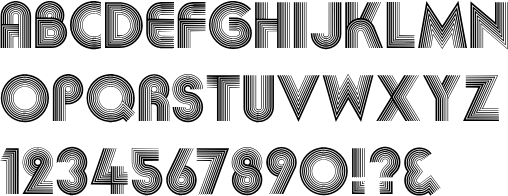
マイクロソフトの初代ロゴで使われた書体「アキラインズ」。「Computational
Geometry Lab」によると、日本人によるデザインのようです。本来、
オルタネートが存在しますが、デジタル化はされていません。現在は 「Linea」
とリネームされたフォントが販売され、「Akka」という無料のクローンフォントもあります。
| Microsoft Logotype in 1975 |
Aki Lines |
| Designers |
: |
Akihiko Seki |
| Year |
: |
1970 |
| Foundry |
: |
ITC |
| Digital |
: |
Linea
Akka |
Category |
: |
Lines |